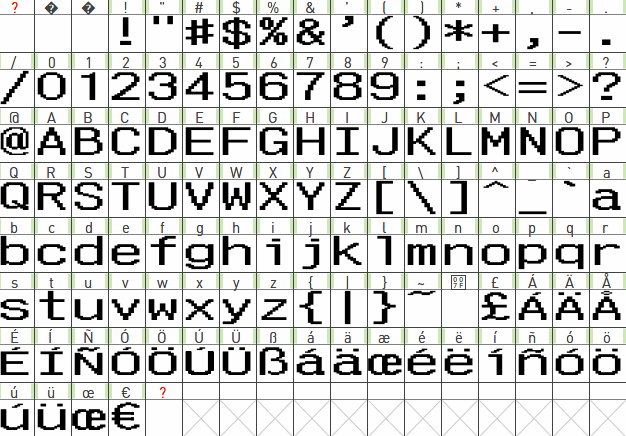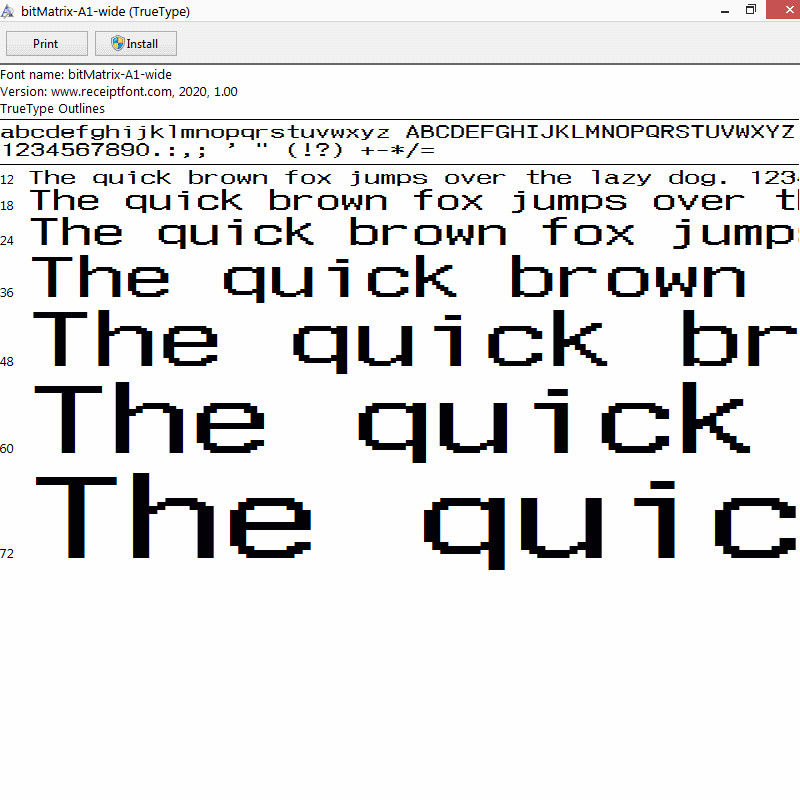
bitMatrix-A1-wide — 영수증·POS 프린터용 전문 글꼴입니다. 결제 후 바로 다운로드할 수 있습니다. ₩56,300 bitMatrix-A1-wide — 영수증·POS 프린터용 전문 글꼴입니다. 결제 후 바로 다운로드할 수 있습니다. 장바구니에 담기 카테고리: 글꼴 스토어 태그: bitMatrix-A1 상품 설명 상품 설명 인쇄된 샘플1: 인쇄된 샘플2: 관련 상품 bitMatrix-A1 ₩93,800 장바구니에 담기 bitMatrix-A1-bold ₩56,300 장바구니에 담기 bitMatrix-A1-narrow ₩56,300 장바구니에 담기